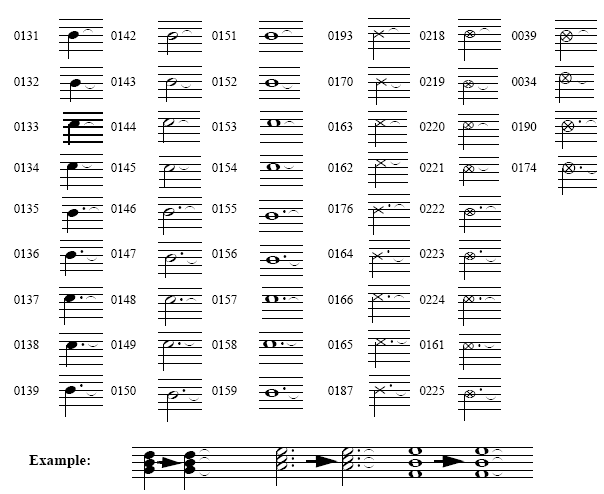
Queste sono teste di note con una legatura sulla destra indicante che la nota deve essere lasciata risuonare. Poiché il simbolo di lasciar vibrare è direttamente attaccato alla testa della nota, utilizzando queste particolari teste di nota risulta più semplice e uniforme inserire questo tipo di notazione. È possibile accedere a questo tipo di notazione utilizzando uno degli Strumenti speciali (quello per cambiare la testa delle note). Prima dovete immettere le note utilizzando uno qualsiasi dei metodi di Finale, quindi dovete cambiare le teste delle note con lo Strumenti Speciali.
Disponibili soltanto nei font Engraver Font Sete Engraver Font Extras
Sono anche inclusi i due simboli di “lasciar vibrare” per il loro inserimento con lo Strumento per le articolazioni.